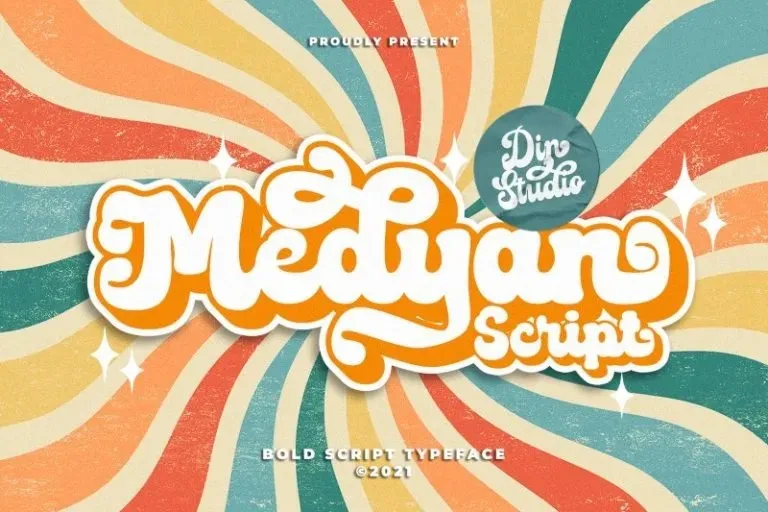
Medyan Font é uma elegante tipografia script bold que remete aos anos 60, proporcionando um toque nostálgico à sua obra. Criada pelo designer Din Studio na plataforma de desafios de ideias 99designs, esta fonte oferece letras grosas e angulares, que são atraentes tanto para olhar quanto leitura. Seu formato angular e as opções extrudadas tornam Medyan Script ainda mais especial. Perfeita para criar cabeçalhos impressionantes, logotipos, menus de sites, gráficos para mídias sociais e muito mais, esta fonte é uma excelente escolha para designers que buscam um estilo retro moderno. Medyan Font é a solução perfeita para quem busca uma tipografia script bold com um toque nostálgico dos anos 60.